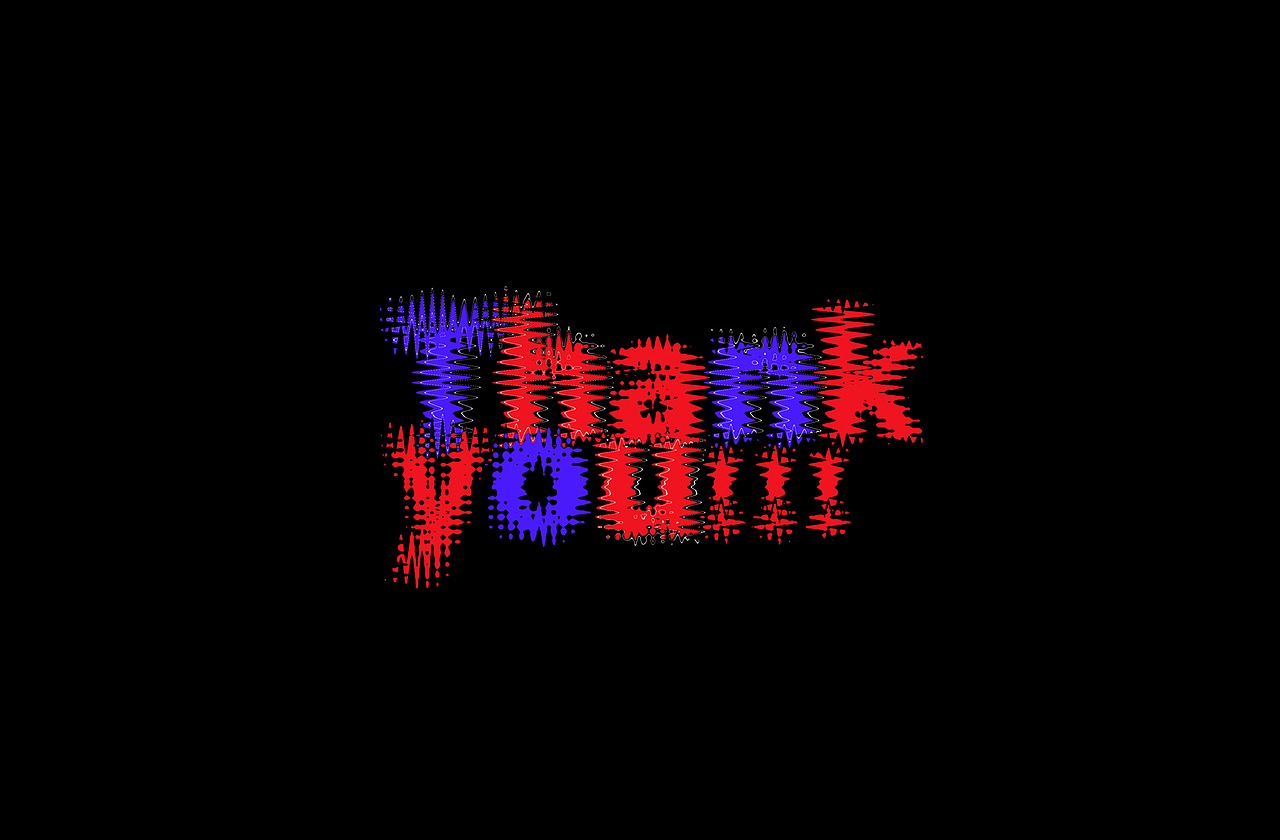
写在前面
关于字体设计也是设计师需要掌握的基本要素,
不管是书籍装帧设计、海报招贴设计,字体的使用都是尤为重要的。
在刚过去的2018年里我们不难发现,字体式海报占据了海报设计的半壁江山,
一些展览海报广告招贴广泛使用字体创意来做主视觉。
所以我也对此进行了针对性的练习,
选择了一些老街地名和书名来做字体设计和创意板式的训练。